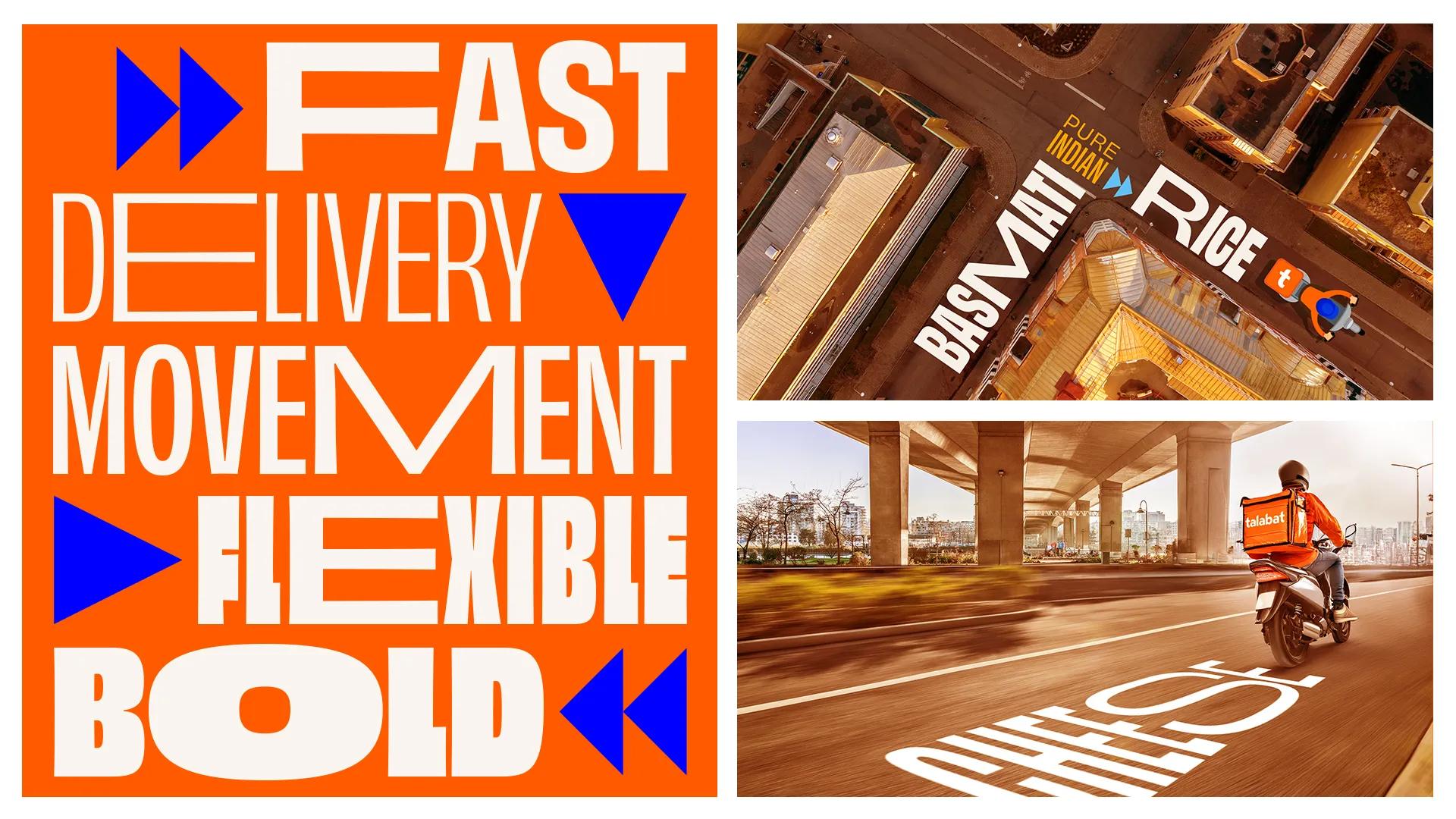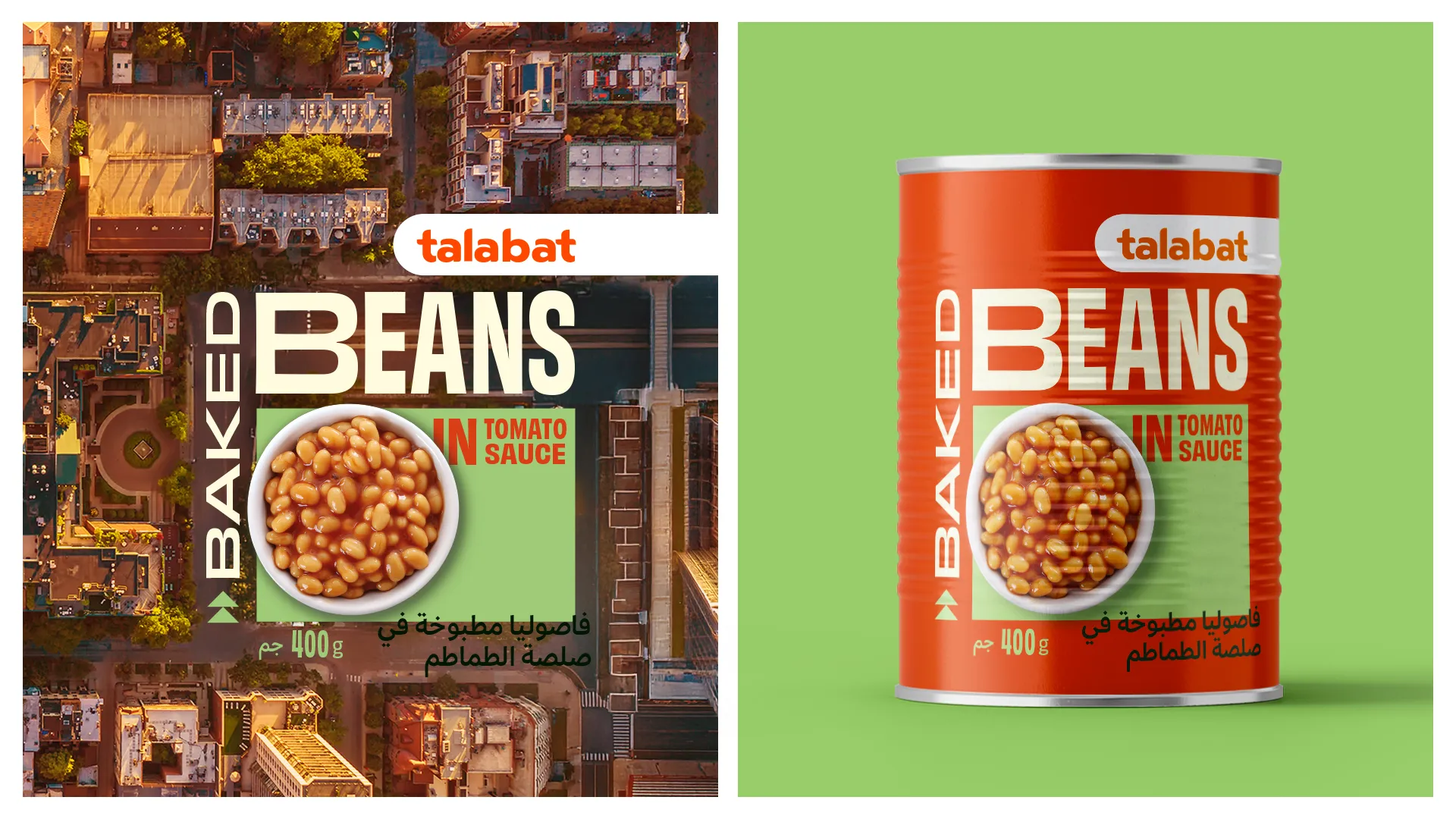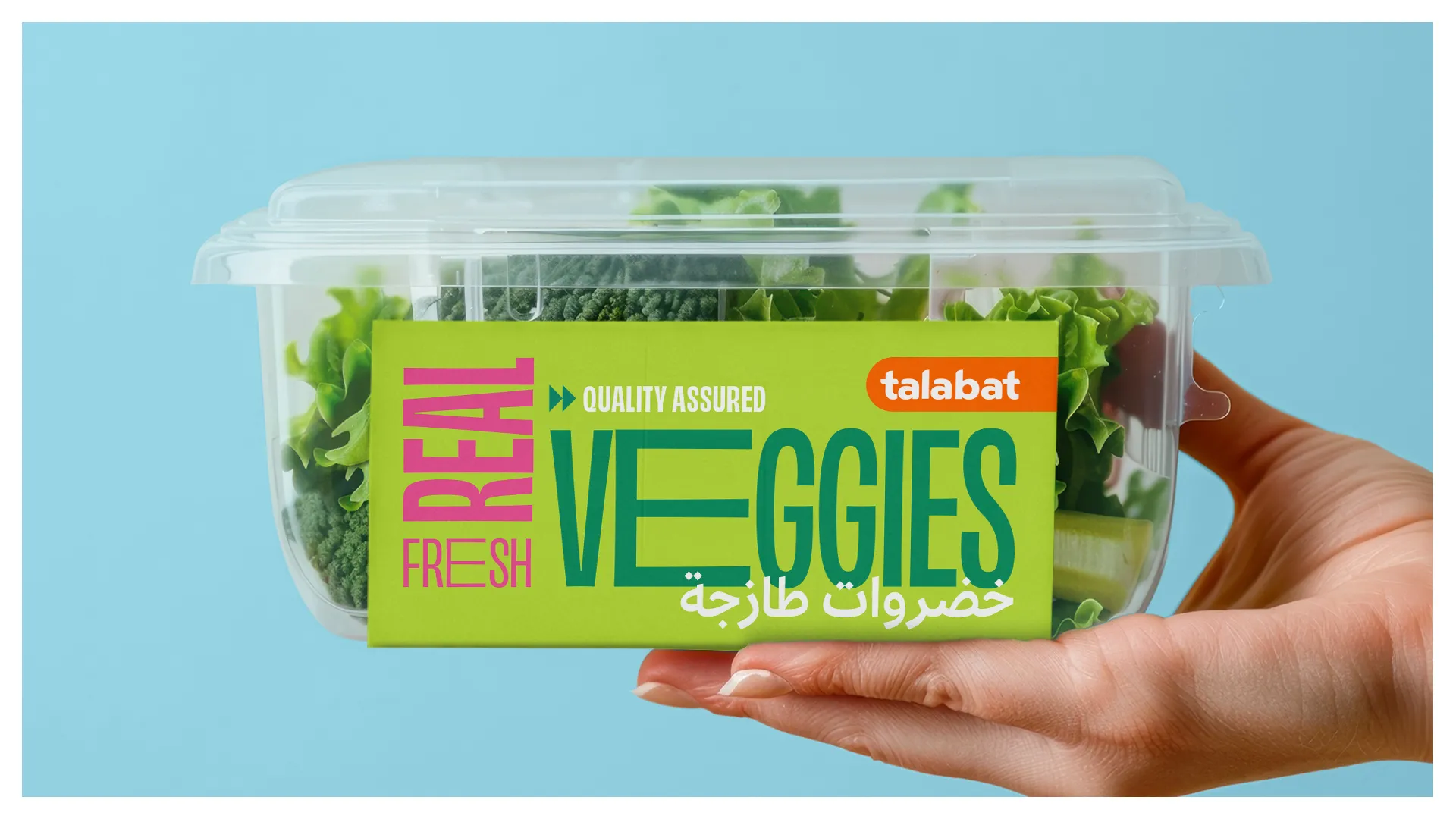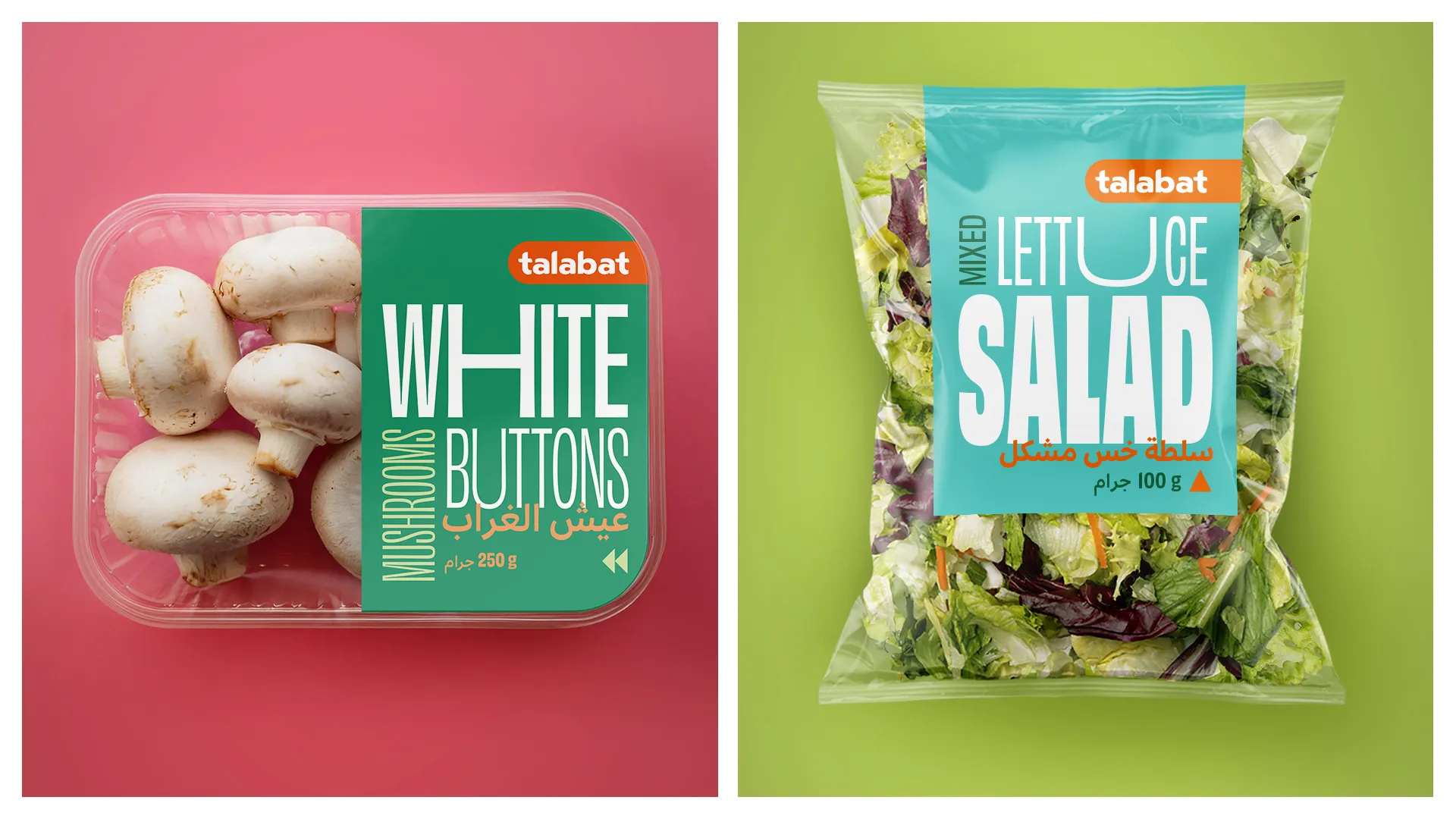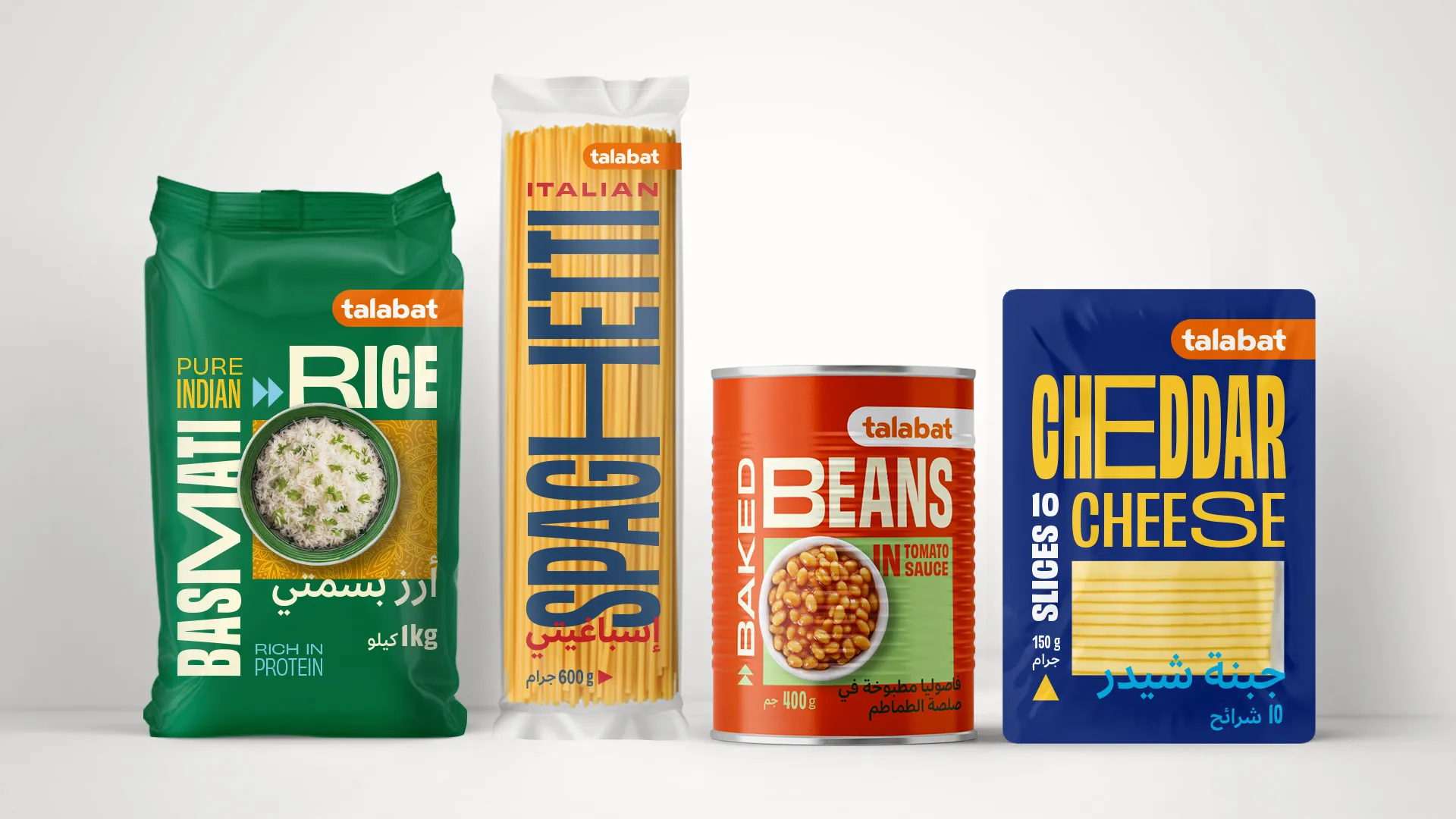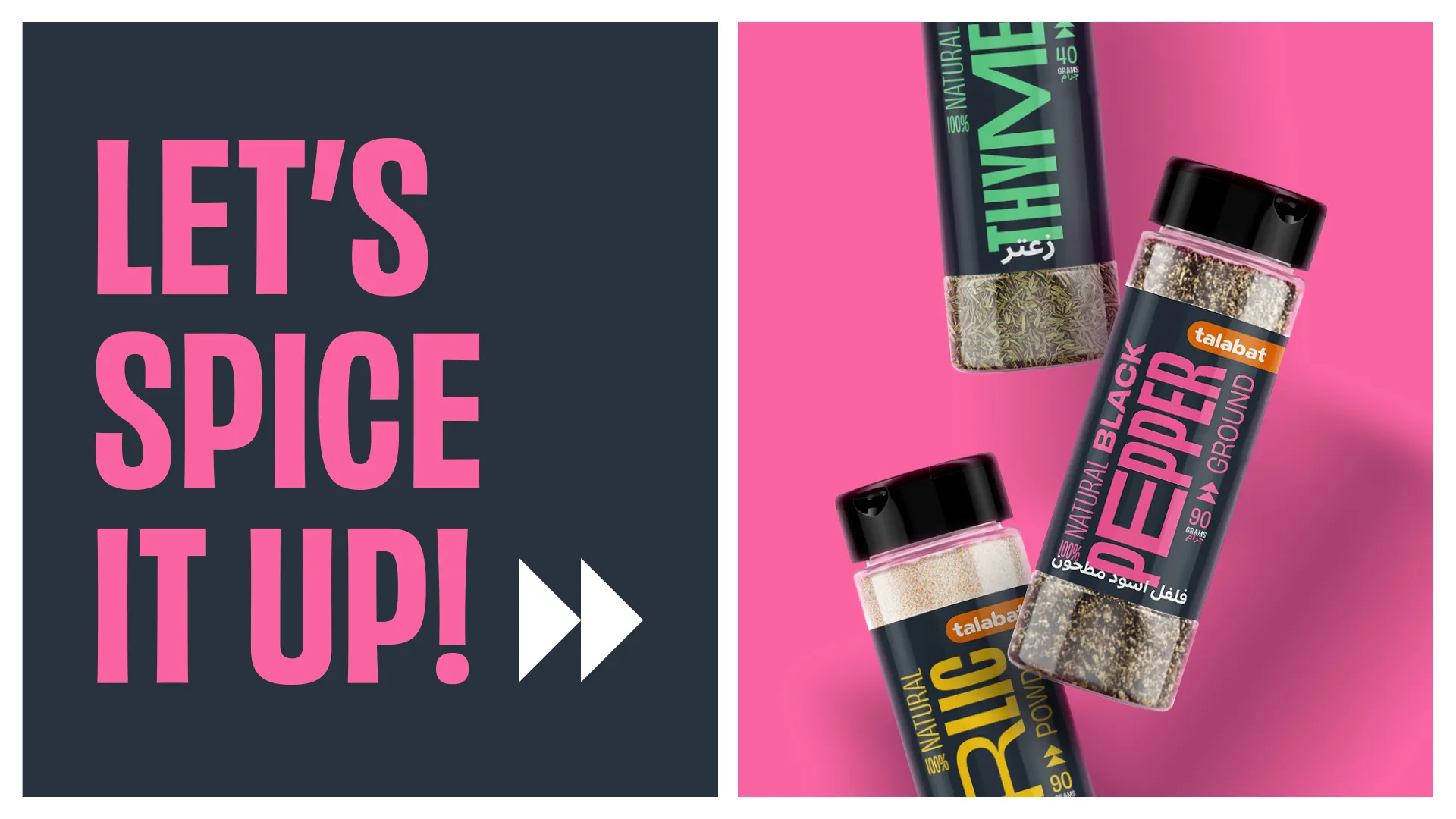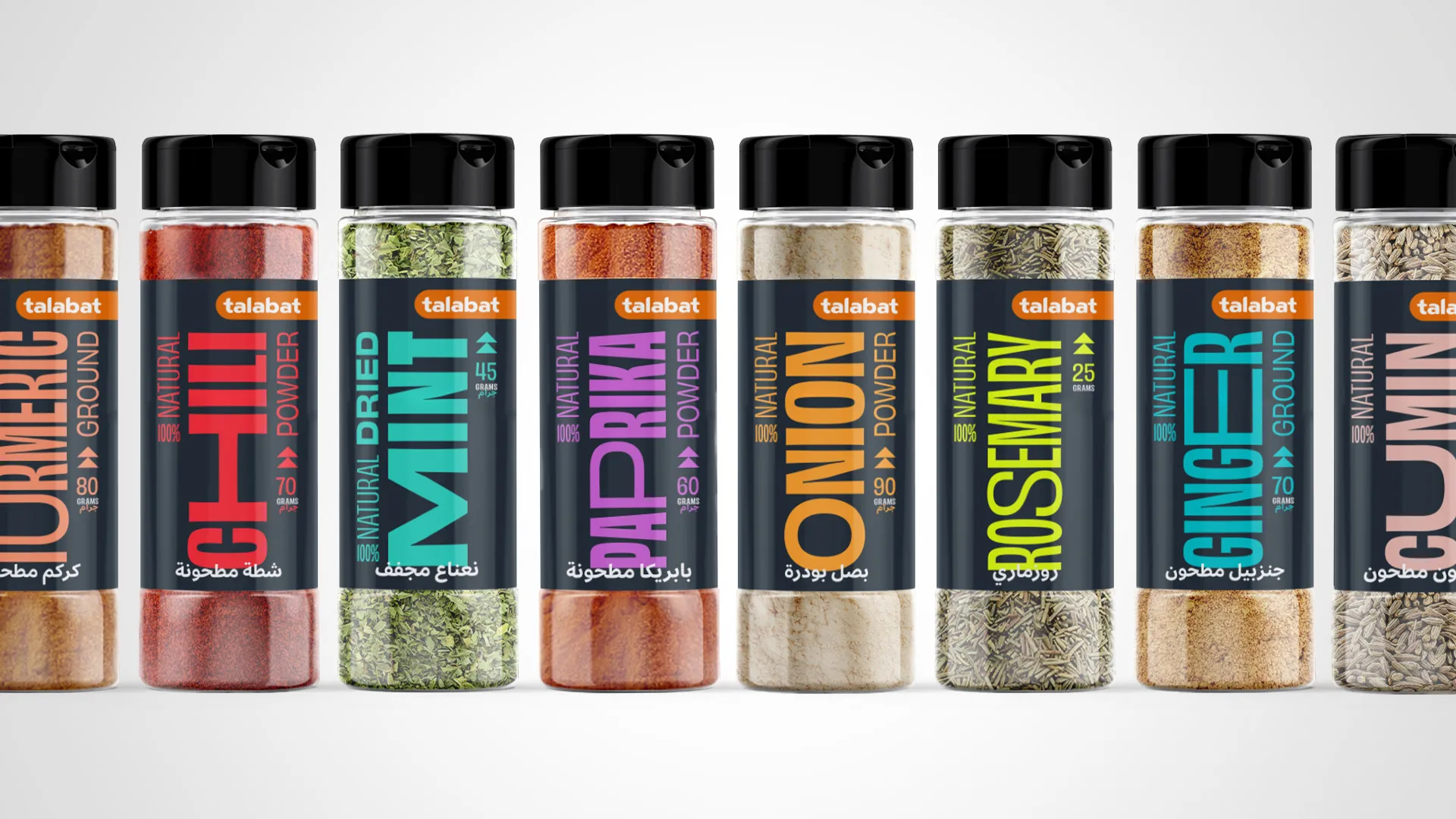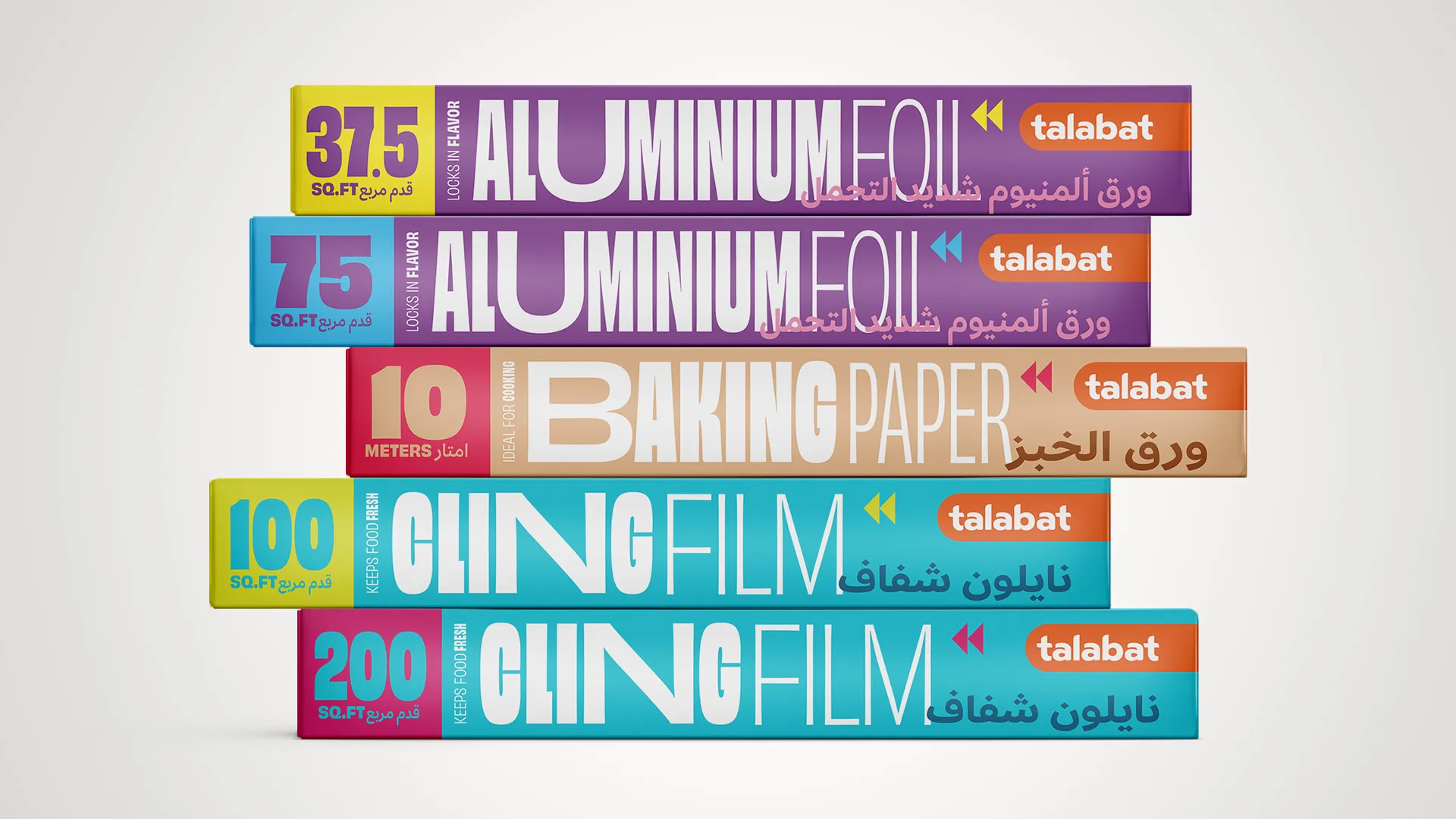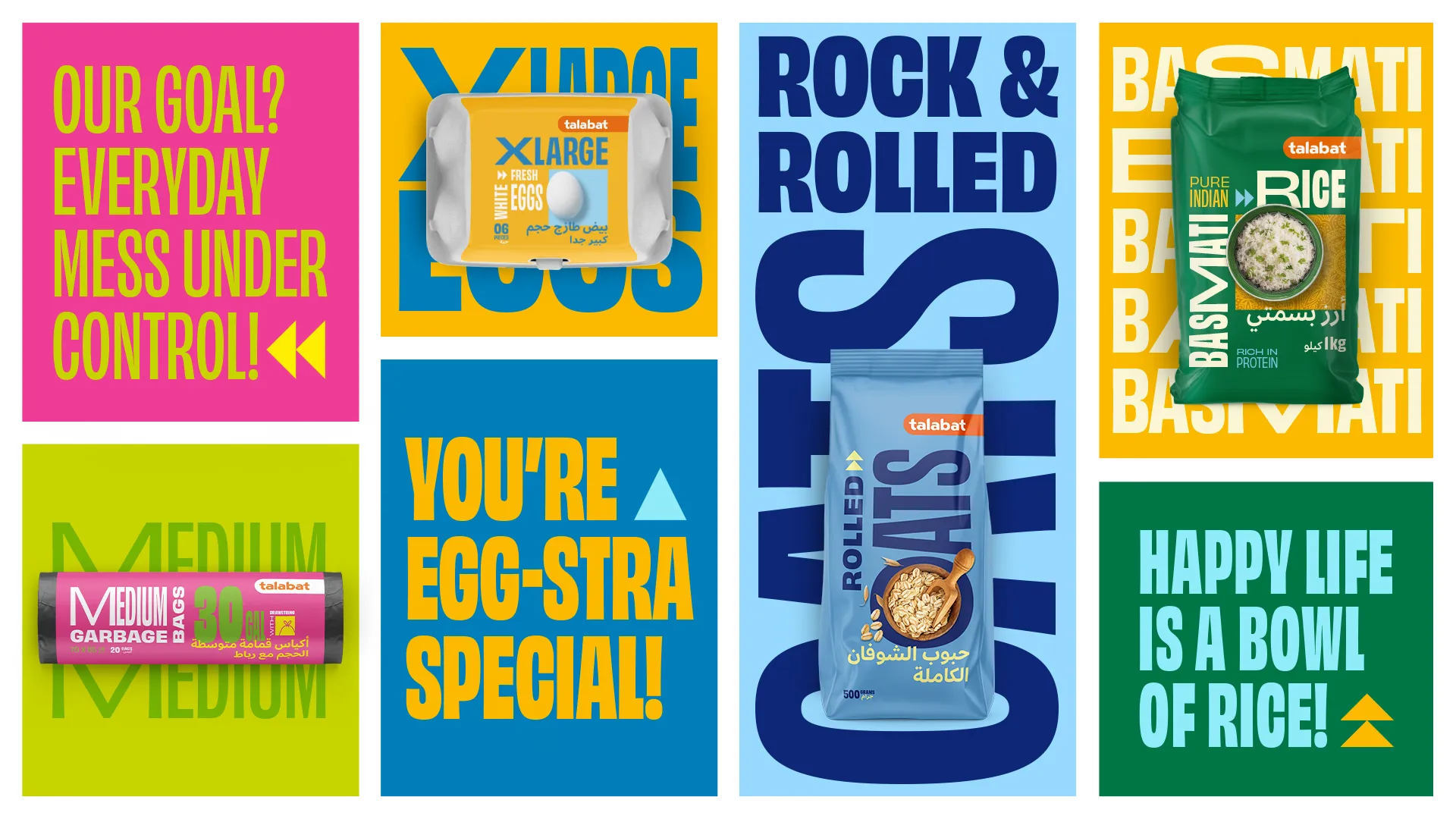
Вариативный шрифт, яркие цвета и дерзкие фразы в дизайне СТМ Talabat от Daymon Design
Сервис доставки Talabat переосмыслил визуальный стиль СТМ, сделав акцент на движении, смелой типографике и максимальной читаемости в онлайн-пространстве
Talabat — ведущая платформа быстрой доставки и крупнейший сервис доставки еды на Ближнем Востоке, базирующийся в Дубае. Недавно компания инициировала перезапуск собственной торговой марки, чтобы закрепить за собой статус самой быстрой службы доставки в регионе с амбициозной целью — доставлять заказы в течение 20 минут с помощью собственного автопарка. Для реализации этой стратегии Talabat поставила задачу полностью переосмыслить визуальную айдентику частного бренда, сделав её воплощением новой продуктовой и сервисной миссии.
Благодаря своей масштабной логистической сети и характерному оранжевому флоту, Talabat уже является одной из самых заметных компаний в городской среде Дубая. Это создало серьёзный задел в узнаваемости, который можно было усилить. Концепция нового дизайна основывается на метафоре движения по городским улицам.
Основу упаковки формирует графическая структура, вдохновлённая видом сверху на гипотетический город — с улицами, кварталами и домами. Эта сетка в стиле Google Maps задаёт модульный принцип верстки элементов. «Здания» и «дороги» заполняются названиями продуктов и их характеристиками, фотографии интегрируются как ориентиры и визуальные доминанты.
Каждая этикетка уникальна — как будто она сгенерирована из разных участков карты, отсылая к идее доставки по разным адресам. Такая гибкая система позволяет сохранить узнаваемую идентичность, при этом визуально дифференцируя линейки внутри бренда. Ключевым элементом упаковки выступает типографика: вытянутые буквы визуализируют скорость и динамику доставки, тексты огибают углы кварталов, а стрелки усиливают направление движения.
Увеличенный кегль и выразительный шрифт обеспечивают превосходную читаемость в цифровом формате — особенно важно, поскольку продукция Talabat Private Brand продаётся исключительно онлайн. Этикетки остаются разборчивыми даже в миниатюрных иконках на экранах смартфонов, выигрывая конкуренцию у других брендов на платформе.
Продуктовые карточки на платформе оформлены в виде баннеров, в которых раскрываются отдельные визуальные элементы и ключевые сообщения с упаковки, помогая пользователям быстрее воспринимать преимущества товара. Коммуникационный стиль Talabat традиционно отличает дерзость, юмор и игривость — и частный бренд должен был говорить тем же языком. Палитра упаковки — яркая, контрастная и энергичная, нацеленная на молодую аудиторию, которой важна эмоциональная вовлечённость и визуальная смелость.
Каждый продукт сопровождается креативной фразой, вызывающей улыбку и играющей с повседневными ситуациями. Эти сообщения не только формируют эмоциональную связь, но и создают эффект сюрприза при первом физическом контакте с продуктом дома.
С учётом культурного многообразия региона и доминирующих языков — английского и арабского — упаковка выполнена с двуязычной системой, учитывающей особенности обоих алфавитов и визуальные привычки пользователей.
Благодаря собственному автопарку и скорости доставки, которая зачастую превосходит поход в ближайший магазин, Talabat уверенно позиционирует свою частную марку как самый быстрый бренд в ОАЭ.